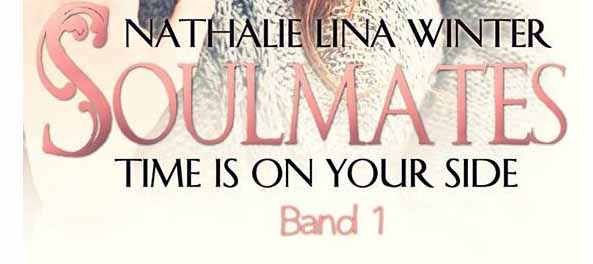
Nachbau Buchcover. Kennt jmd. die Schriften?
Kennt jemand vielleicht eine / mehrere dieser Schriftarten?
Das verzierte S kenne ich nicht, aber es sieht so aus, als ob hier die Garamond
die Basis geliefert hätte. Möglicherweise ist das Handarbeit?
OULMATES sieht nach einer misshandelten, gequetschten Garamond aus.
Wirf mal einen Blick auf die Apple Garamond. Diese könnte dafür missbraucht
worden sein.
Der Rest hat starke Ähnlichkeit mit Rudolf Kochs Stahl, aber das R passt nicht.
Meine Unterlagen laufen ins Leere. Wirf mal einen Blick auf folgende Schriften:
Lydian, CG Lisbon, AFD Libris ... Bei allen passt das R nicht. :-(